Google Fonts được tạo ra với mục tiêu làm cho web trở nên đẹp hơn, nhanh hơn và mở hơn. Các phông chữ trong thư viện này được thiết kế để mang lại trải nghiệm tốt nhất cho người dùng. Đồng thời đảm bảo tính khả dụng và khả năng tiếp cận của thiết kế. Bài viết này sẽ tìm hiểu chi tiết về Google Fonts và cách sử dụng nó.
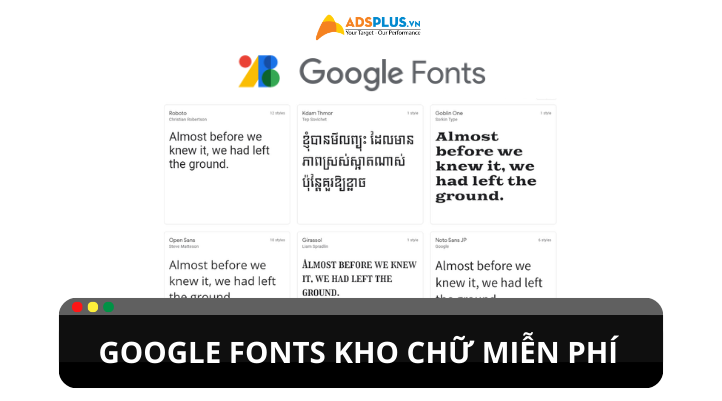
Giới thiệu về Google Fonts
Google Fonts là một thư viện phông chữ mở, miễn phí, chất lượng cao từ Google. Thư viện này bao gồm hơn 1.300 phông chữ từ nhiều nhà thiết kế và nhà sáng tạo trên toàn thế giới. Các phông chữ trong Google Fonts có thể được sử dụng trên các trang web, ứng dụng và các dự án khác.
Google Fonts được tạo ra với mục đích giúp các nhà thiết kế và nhà phát triển web tạo ra các trang web và ứng dụng đẹp hơn, hấp dẫn hơn. Phông chữ Google được thiết kế để hoạt động tốt trên nhiều loại thiết bị và kích thước màn hình, và chúng được tối ưu hóa cho hiệu suất web.
Lợi ích khi sử dụng Google Fonts
Miễn phí và dễ sử dụng
Đa dạng
Google Fonts cung cấp một loạt các phông chữ khác nhau, từ các phông chữ sans serif hiện đại đến các phông chữ serif cổ điển. Điều này cho phép bạn tạo một trang web có tính thẩm mỹ phù hợp với thương hiệu của mình.
Hiệu suất cao
Google Fonts được tối ưu hóa để tải về nhanh chóng và hiệu quả. Điều này có thể giúp cải thiện tốc độ tải trang của website.
Tăng tính thẩm mỹ cho trang web
Google Fonts có thể giúp trang web của bạn trở nên đẹp mắt và chuyên nghiệp hơn. Các phông chữ khác nhau có thể tạo ra những hiệu ứng khác nhau, vì vậy bạn có thể lựa chọn những phông chữ phù hợp với phong cách của trang web của mình.
Tăng tính dễ đọc
Phông chữ phù hợp có thể giúp cải thiện khả năng đọc hiểu của người dùng. Các phông chữ dễ đọc thường có kích thước và độ dày phù hợp, cũng như độ tương phản cao với nền tảng.
Tăng khả năng nhận diện thương hiệu
Phông chữ là một phần quan trọng của nhận diện thương hiệu. Sử dụng cùng một phông chữ trên tất cả các tài liệu của bạn, bao gồm trang web, logo và tài liệu in, có thể giúp tạo sự nhất quán và xây dựng nhận thức về thương hiệu của bạn.
Phân loại Google Fonts
Google Fonts có thể được chia thành 5 loại chính:
Sans serif
Đây là loại phông chữ phổ biến nhất, có các nét thẳng và thanh mảnh. Sans serif thường được sử dụng cho văn bản dài, vì chúng dễ đọc và dễ nhìn. Một số phông chữ sans serif phổ biến của Google Fonts bao gồm Roboto, Open Sans và Lato.
Serif
Loại phông chữ này có các nét thanh mảnh kết thúc bằng các nét nhỏ, cong. Serif thường được sử dụng cho văn bản có độ trang trọng cao, chẳng hạn như văn bản in sách và báo. Một số phông chữ serif phổ biến của Google Fonts bao gồm Georgia, Times New Roman và Baskerville.
Monoline
Loại phông chữ này có các nét đều nhau, không phân biệt giữa nét thanh và nét đậm. Monoline thường được sử dụng cho văn bản kỹ thuật, chẳng hạn như mã nguồn và biểu đồ. Một số phông chữ monoline phổ biến của Google Fonts bao gồm Courier New, monospace và Consolas.
Script
Loại phông chữ này có các nét uốn lượn, mềm mại. Script thường được sử dụng cho văn bản nghệ thuật, chẳng hạn như tiêu đề và lời mời. Một số phông chữ script phổ biến của Google Fonts bao gồm Brush Script MT, Zapfino và Copperplate.
Decorative
Loại phông chữ này có các nét đặc biệt, độc đáo. Decorative thường được sử dụng cho văn bản trang trí, chẳng hạn như tiêu đề và logo. Một số phông chữ decorative phổ biến của Google Fonts bao gồm Comic Sans MS, Papyrus và Curlz MT.
Một số phông chữ Google Fonts phổ biến nhất
- Roboto: Phông chữ sans serif hiện đại, được sử dụng bởi Google trên nhiều sản phẩm của mình.
- Open Sans: Phông chữ sans serif hiện đại, dễ đọc và được sử dụng rộng rãi trên các website.
- Lato: Phông chữ sans serif hiện đại, nhẹ nhàng và thanh thoát.
- Oswald: Phông chữ sans serif hiện đại, đậm và mạnh mẽ.
- Slabo 27 px: Phông chữ sans serif hiện đại, lớn và dễ đọc.
- Roboto Condensed: Phông chữ sans serif hiện đại, có chiều rộng hẹp.
- Montserrat: Phông chữ sans serif hiện đại, có các góc bo tròn.
- Source Sans Pro: Phông chữ sans serif hiện đại, được thiết kế cho màn hình máy tính.